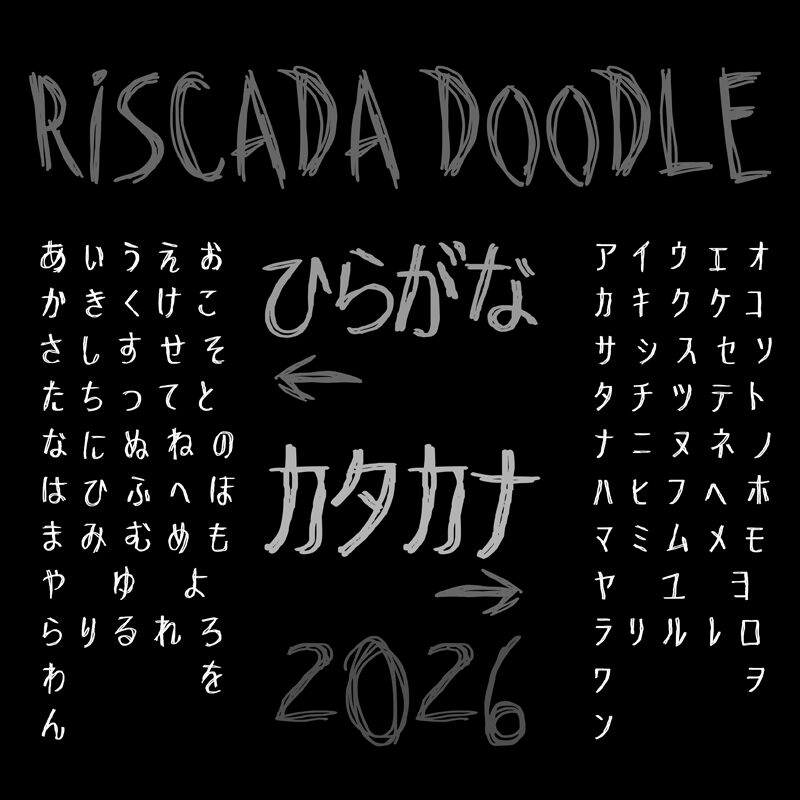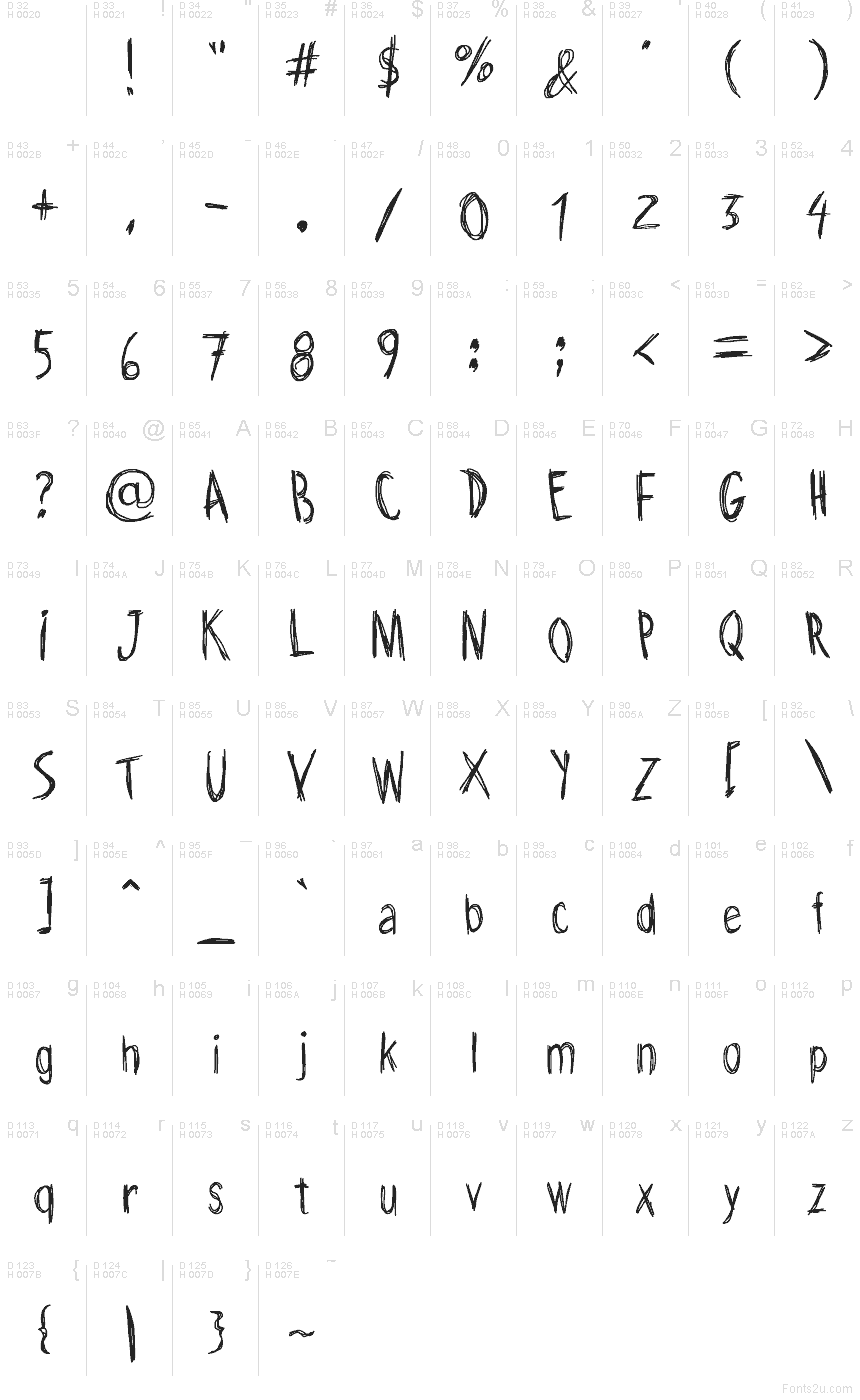
Riscada Doodle Ktkn od Galdino Otten Fonts je bezplatné skriptové písmo ve stylu trash s vysokými, drátovitými literami a záměrně neuspořádanými obrysy. Opakované tahy se podél tvarů chvějí jako uspěchané črty perem. Výsledek působí syrově a nervózně.
Nezávislé hudební vydavatelství nebo undergroundový klub ho mohou využít pro plakáty, branding a propagační předměty s drsným nádechem DIY. Jeho vyškrabávaná kresba se hodí také pro hororovou grafiku a rebelské mládežnické projekty určené publiku, které dává přednost domácké vizualitě před uhlazeným písmem.